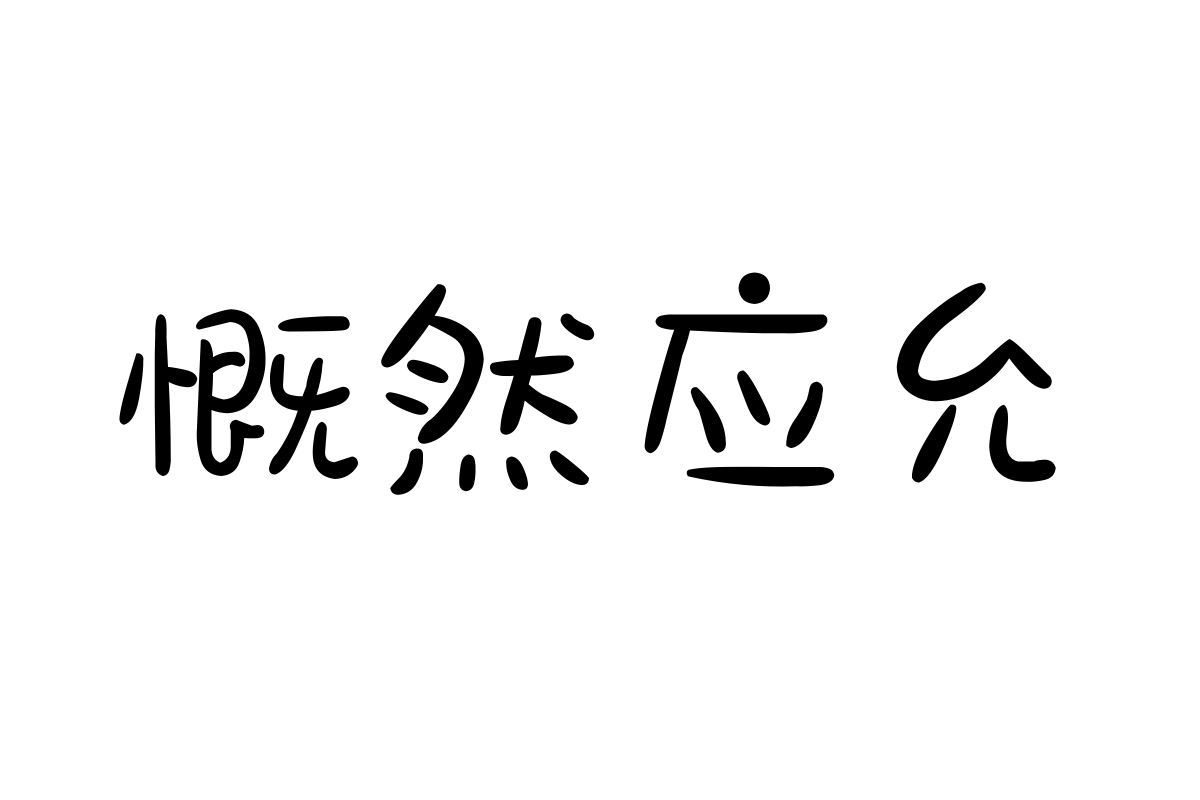
字体管家甜甜圈是一款免费的中文字体,由字体管家团队开发。这款字体具有可爱的设计风格,适用于各种设计场景,如广告、海报、包装等。甜甜圈字体的特点是圆润可爱,线条流畅,给人一种温馨的感觉。同时,字体的笔画粗细适中,适合用于需要强调的部分,如标题或重要信息。此外,甜甜圈字体还支持多种字重和字形,可以根据设计需求进行个性化调整。